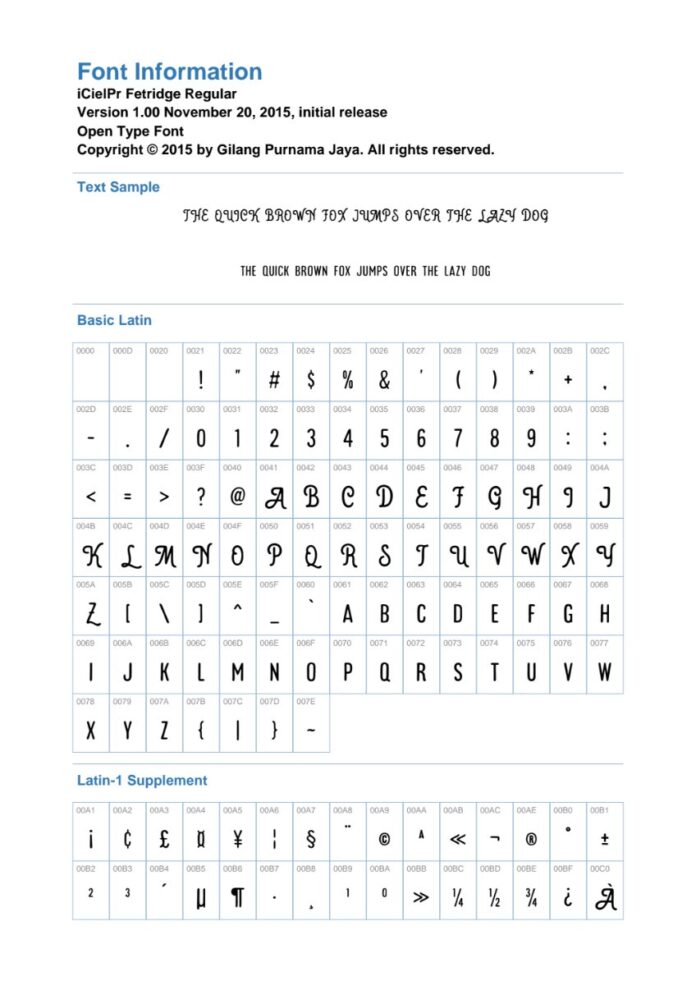
Font Chữ Fetridge Đẹp Mắt
Font Chữ Fetridge Đẹp Mắt. Khám phá font chữ Fetridge – một lựa chọn tuyệt vời cho các dự án thiết kế sáng tạo. Với phong cách độc đáo, Fetridge phù hợp cho logo, tiêu đề và nhiều ứng dụng khác, mang lại vẻ đẹp tinh tế và chuyên nghiệp cho mọi tác phẩm của bạn.
Trong thế giới thiết kế đồ họa đầy màu sắc, việc lựa chọn một font chữ phù hợp có thể tạo nên sự khác biệt lớn cho tác phẩm của bạn. Hôm nay, Poster.vn hân hạnh giới thiệu đến bạn một tài nguyên font chữ độc đáo và đầy cảm hứng: Font Fetridge. Với phong cách riêng biệt, Fetridge không chỉ là một font chữ mà còn là một công cụ mạnh mẽ giúp bạn truyền tải thông điệp một cách ấn tượng và chuyên nghiệp.
Giới thiệu về Font Fetridge
Font Fetridge là một kiểu chữ được thiết kế với sự kết hợp hài hòa giữa nét cổ điển và hiện đại. Với các đường nét mềm mại nhưng vẫn giữ được sự mạnh mẽ, Fetridge mang đến một vẻ ngoài thanh lịch và tinh tế. Đây là một lựa chọn lý tưởng cho những ai đang tìm kiếm một font chữ có khả năng tạo điểm nhấn mạnh mẽ mà không làm mất đi sự sang trọng.
Được phát triển bởi iCielPr Fetridge Regular, phiên bản 1.00 ra mắt vào ngày 20 tháng 11 năm 2015, Fetridge là một font Open Type, đảm bảo khả năng tương thích rộng rãi trên nhiều nền tảng và phần mềm thiết kế khác nhau. Bản quyền thuộc về Gilang Purnama Jaya, khẳng định chất lượng và sự độc đáo của font chữ này.
Đặc điểm nổi bật của Font Fetridge
• Phong cách độc đáo: Fetridge sở hữu một phong cách viết tay đặc trưng, mang lại cảm giác cá nhân hóa và nghệ thuật cho mọi thiết kế.
• Dễ đọc: Mặc dù có phong cách riêng, các ký tự của Fetridge vẫn được thiết kế rõ ràng, dễ đọc, đảm bảo thông điệp của bạn được truyền tải hiệu quả.
• Đa dạng ứng dụng: Từ thiết kế logo, tiêu đề, poster, thiệp mời cho đến các ấn phẩm quảng cáo, Fetridge đều có thể phát huy tối đa vẻ đẹp của mình.
• Hỗ trợ ký tự đa dạng: Font chữ này hỗ trợ đầy đủ các ký tự Latin cơ bản và bổ sung Latin-1, giúp bạn dễ dàng sử dụng trong nhiều ngôn ngữ khác nhau.
Ứng dụng của Font Fetridge trong thiết kế
Font Fetridge có thể được ứng dụng linh hoạt trong nhiều loại hình thiết kế khác nhau, mang lại hiệu quả thẩm mỹ cao:
Thiết kế Logo và Nhận diện thương hiệu
Với vẻ ngoài độc đáo và tinh tế, Fetridge là một lựa chọn tuyệt vời cho việc thiết kế logo. Nó giúp tạo ra một thương hiệu có cá tính riêng, dễ nhận biết và để lại ấn tượng sâu sắc trong tâm trí khách hàng. Các doanh nghiệp muốn thể hiện sự sáng tạo, sang trọng và khác biệt có thể cân nhắc sử dụng Fetridge cho bộ nhận diện của mình.
Thiết kế Tiêu đề và Tiêu đề phụ
Trong các ấn phẩm như poster, banner, tạp chí hay website, việc sử dụng Fetridge cho tiêu đề sẽ giúp thu hút sự chú ý ngay lập tức. Các đường nét mềm mại nhưng rõ ràng của font chữ này làm cho tiêu đề trở nên nổi bật và dễ đọc, khuyến khích người xem tiếp tục khám phá nội dung.
Thiết kế Thiệp mời và Ấn phẩm cá nhân
Fetridge đặc biệt phù hợp cho các thiết kế mang tính cá nhân hóa như thiệp cưới, thiệp sinh nhật, thiệp chúc mừng. Nó mang lại cảm giác ấm áp, thân thiện và sang trọng, giúp truyền tải thông điệp yêu thương một cách chân thành nhất.
Thiết kế Bao bì sản phẩm
Đối với các sản phẩm cao cấp, thủ công hoặc có tính nghệ thuật, Fetridge có thể được sử dụng trên bao bì để tăng thêm giá trị thẩm mỹ và sự độc đáo. Nó giúp sản phẩm nổi bật trên kệ hàng và thu hút khách hàng mục tiêu.
• Kết hợp với font chữ đơn giản: Vì Fetridge đã có phong cách khá mạnh mẽ, bạn nên kết hợp nó với các font chữ sans-serif hoặc serif đơn giản, sạch sẽ cho phần nội dung chính để tạo sự cân bằng và dễ đọc.
• Sử dụng kích thước phù hợp: Fetridge thường đẹp nhất khi được sử dụng ở kích thước lớn cho tiêu đề hoặc các điểm nhấn. Khi dùng ở kích thước nhỏ hơn, hãy đảm bảo độ tương phản tốt để tránh bị khó đọc.
• Màu sắc: Thử nghiệm với các gam màu khác nhau để xem Fetridge thể hiện tốt nhất trong ngữ cảnh nào. Nó có thể trông tuyệt vời với màu đen cổ điển, màu vàng sang trọng hoặc các màu pastel nhẹ nhàng.
Font Fetridge có hỗ trợ tiếng Việt không?
Font Fetridge hỗ trợ các ký tự Latin cơ bản và bổ sung Latin-1. Để biết chính xác font có hỗ trợ đầy đủ các dấu tiếng Việt hay không, bạn nên kiểm tra bảng ký tự hoặc thử nghiệm trực tiếp trong phần mềm thiết kế của mình.